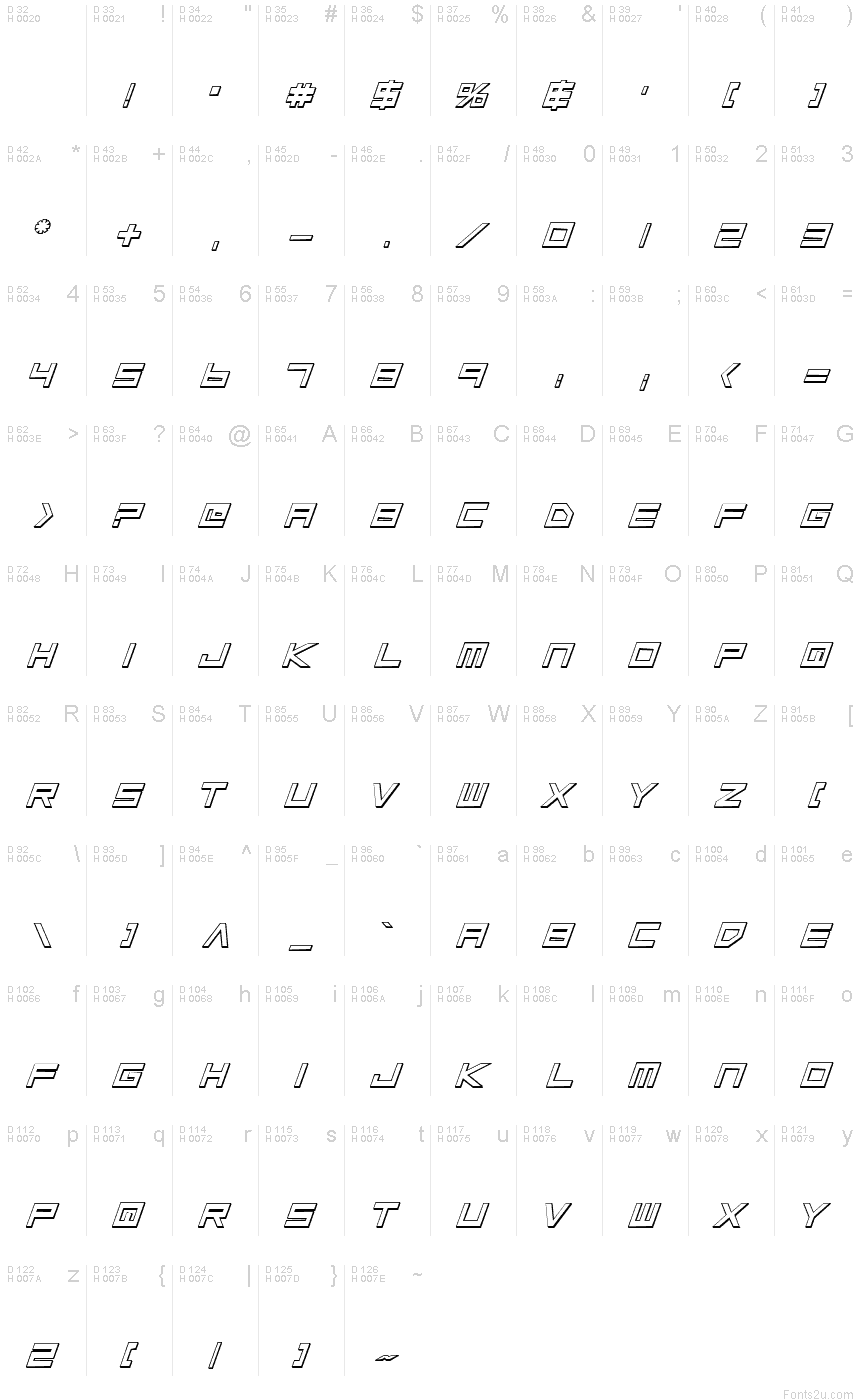
Low Gun Screen Bold Italic 3D di Iconian Fonts è un font display techno angolare gratuito, con un taglio veloce ispirato all'era arcade. Le lettere sono costruite con angoli netti e contorni aperti, mentre l'effetto 3D sfalsato conferisce alle maiuscole un look da schermo grafico che sa di fantascienza rétro, piuttosto che di futurismo patinato.
Si adatta perfettamente a loghi di videogiochi, titoli di poster, copertine di mixtape, anteprime per lo streaming e cartelli grafici dove le parole brevi necessitano di un tocco sintetico. Essendo un font gratuito, è particolarmente utile per monogrammi e titoli taglienti, poiché la geometria inclinata e il trattamento 3D scavato fanno gran parte del lavoro visivo ancora prima di aggiungere altro.